思緒重生體由一月中上旬開始眾籌,擱筆之時已募集了目標金額(港幣一百萬元左右)的四成多,思緒重生體的設計師陳靖軒(Roy)創立的「思緒俠造字」帶動,自 2019 年至今透過社交平台上的字體設計作品、不同造字產品,一直致力於推廣繁體字的設計。這套充滿力量的廣告字體是要「呼籲大家不要放棄」,不只是香港人,而是一些逐漸在香港沒落的回憶。取名重生體,並不只是將中文字重生,而是「各行業都在好努力地去召喚大家去傳承,我就希望用重生體幫字體重生,大家以自己方式延續香港靈魂。」
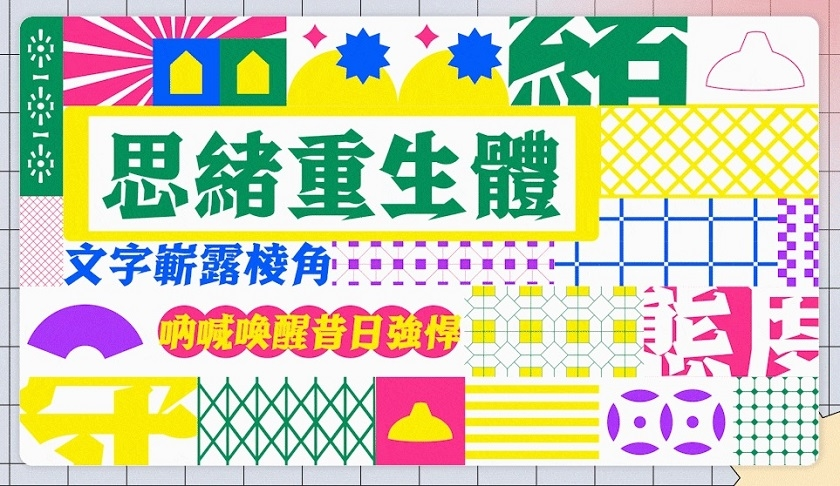
不是夢想
「我不會用『夢想』去形容這套字體,我有很多夢想的,想創造一套字體後可以帶動香港字體界、設計界甚至全世界的改變;但這套字體是一個想法,是讓夢想一步一步實現的想法。」Roy 當初專心一意當上字體設計師也是機緣巧合的事,之前在電影公司做設計師的時候已經希望可以多做一點 typeface 有關的工作,加上他形容自己在用色或排版比較弱,所以「在黑與白的世界會拿捏得好一點。加上以往設計時都想做多一點新鮮的事,所以字體設計適合自己,因為市面上比較少,向難度挑戰。」思緒重生體可說是在風波裏誕生的字體,2019 年尾轉為全職造字的 Roy 還在尋找自己及公司的方向時已有初步的概念,第一個落手做的作品事緣半年後的立法會選舉,雖然委託他的議員最後沒有用上思緒重生體助選,但當時 Roy 都決定重生體要是一套有力量、有號召力的字體;直至 2021 年中,Roy 在異地重拾起這個計劃,不帶任何愁緒、只是純粹地埋首造了一千個常用字,到年尾才認真要如何去做營銷、眾籌希望可以做到一套較為完整的五千多個繁體字;而如果去成功解鎖近九千個繁體字,就要留待眾籌第二階段了。經歷漩渦至今能夠誕生,即使最後達標與否,相信自身都帶着特別的存在價值及意義。
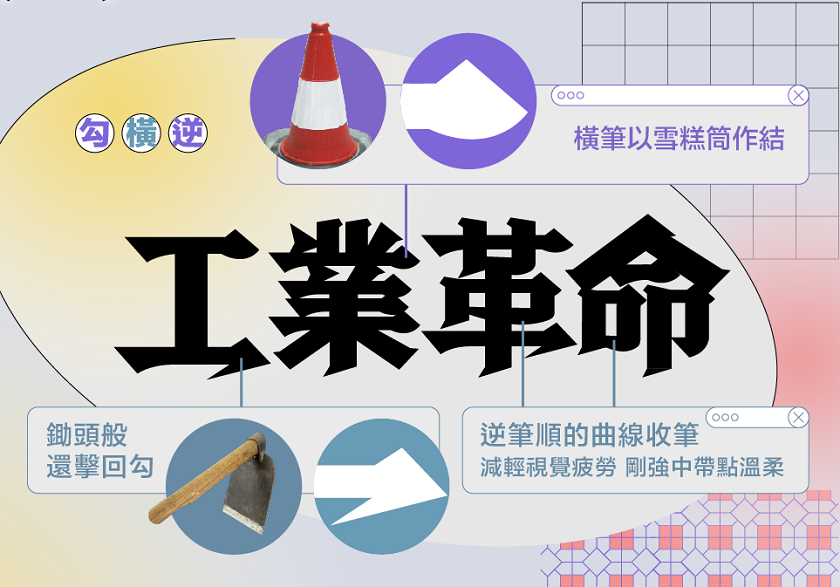
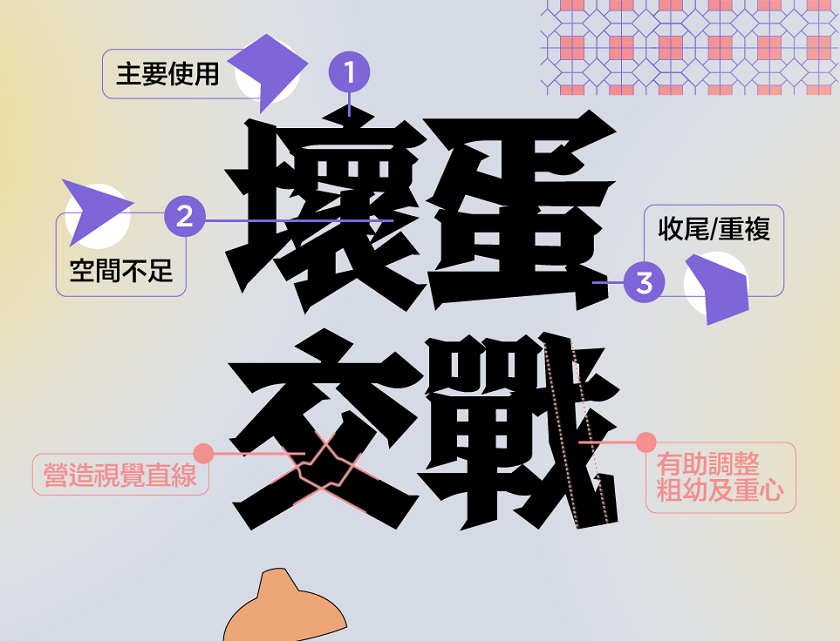
為什麼說思緒重生體很有力量?重生體以宋體為基礎,加入了黑體橫直線粗幼相近的特色;它有鋼筆般銳利的開首,也有像雪糕筒的尾端裝飾,是一個剛中帶柔的意念。重生體的另一個特色是包含了香港口語,例如「哋」、「囉」等,「是特意的,既然決定要做香港字體,就當然要以香港字為先;可能其他眾籌都會有,但要達到某一個限額才會去做,好像要看人家面色似的。」另外,做標題字除了是 Roy 比較強項的一環,他亦考慮到市場上的需求,因為市面上的確較少力量型的字體。「重生體滿足到這個需求,但這個考慮亦緣於我覺得每個字都應有自己展現特性的機會,愈有性格的字對於設計可以幫助更大。」有感而發,是因為 Roy 以往在電影公司的氣餒,就是圖像與字體的強弱不平衡,「即使推出了重生體之後都有批評說字體太強太『搶 fo』(焦點),但野心大一點的說,字體跟圖像的設計不是要相輔相成的嗎?字型進步了,artwork 被搶風頭,不就應該改善它嗎?重生體是由市場的盲點出發,好的設計不少,但就未有一個好的香港字型可以做代表,所以要填補這空格;將重生體放到 artwork 上,圖像變弱就再進步,兩者就可以一起變成優點;希望下年可以見到重生體如何默默改變 artwork。」
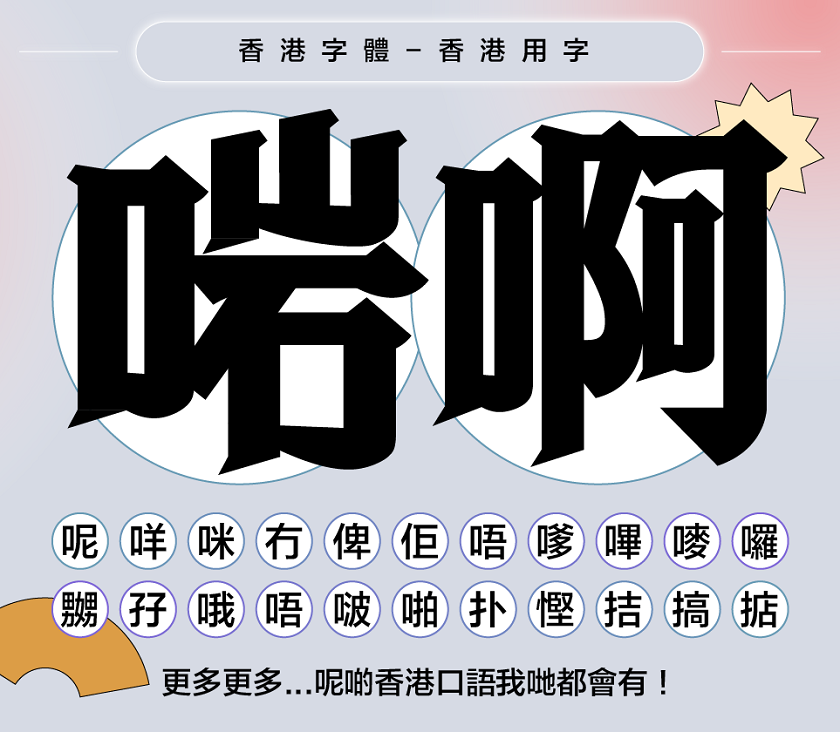
時辰到?
其實 Roy 當初立下決心全職做字體設計師,或多或少都是見到其他在眾籌的設計師的努力而吸引他入行,希望可以為繁體字創出更多不同風格的選擇;但造一整套繁體字,如此大的計劃,說沒有擔心就假的,「但與其因為擔心而卻步,不如說為什麼要堅持下去。香港懂得做又較有資源或營銷經驗的字體設計師不多,如果自己不做,其他有心的人或更年輕的人就少了一個推動。」Roy 的志願仍然是希望改變世界,「更多人見到的東西,改變的速度就會更快;先做了再說吧,不要因為擔心而卻步。」他舉了兩個例子,「電腦未出現之前都未知可以如此改變世界!Mirror 出現之前也可能未覺得香港樂壇可以翻天覆地。」
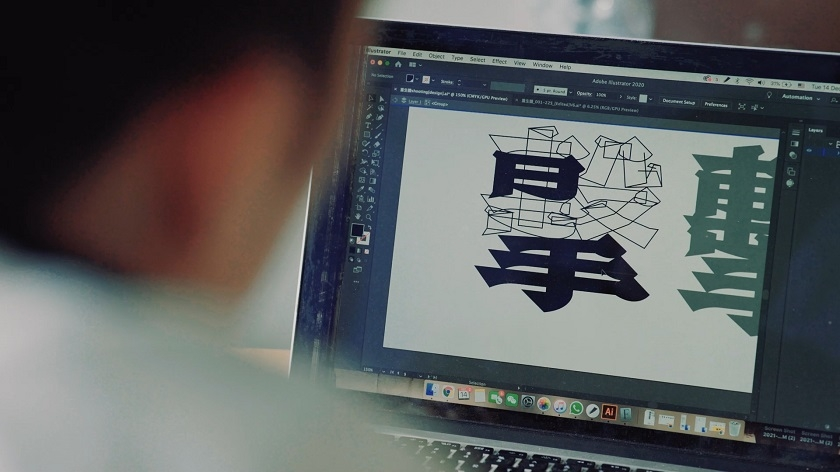
但成功與否、timing 到了與否,其實真的不知道,「香港是成果論吧,『得』就代表 timing 對,失敗就是時辰未到。但即使眾籌失敗了,我都不會覺得真的是『失敗』,到頭來焦頭爛額都可以,一來已盡了力,二來這個計劃可以是將來未出現的計劃的踏腳石,下一位設計師可以參考、可以比我走多一步,最後不一定要是我自己去到對面岸。」改變不是一朝一夕的事,但作為設計師,Roy 自覺有使命,「香港文創圈不乏人才,但生意只能賺取生活或時間上的自由;要真正作出改變,就要『做大』:香港不會因為多了一間字體設計公司而有所改變,但一套字體就不同,這個改變可以是永久的。不是是貢獻什麼,是抱着盡力去試的心態,想嘗試留低一點什麼,亦希望其他人見到原來有前路可走的。」
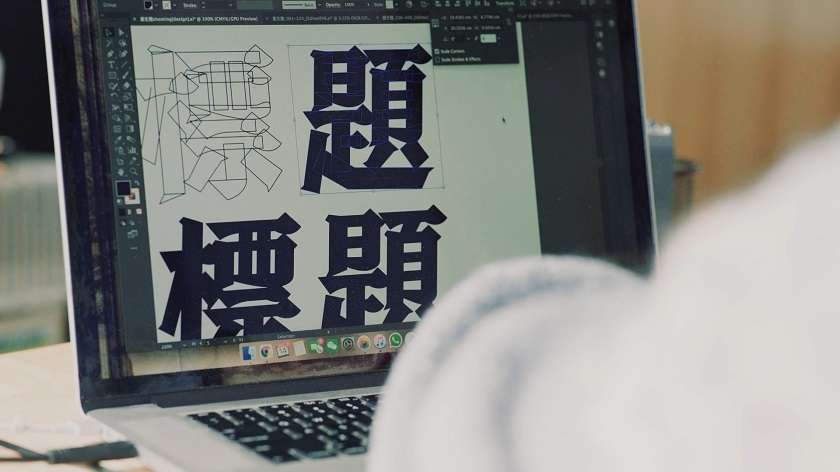
思緒重生體的設計意念是鼓勵大家不要放棄,將香港靈魂、一些正沒落的文化重生,但 Roy 都經常提醒自己,「不要整天幻想改變世界,不如先改變自己。」